Canvaで迷わないフォント選びガイド|用途別に合うフォントだけを厳選
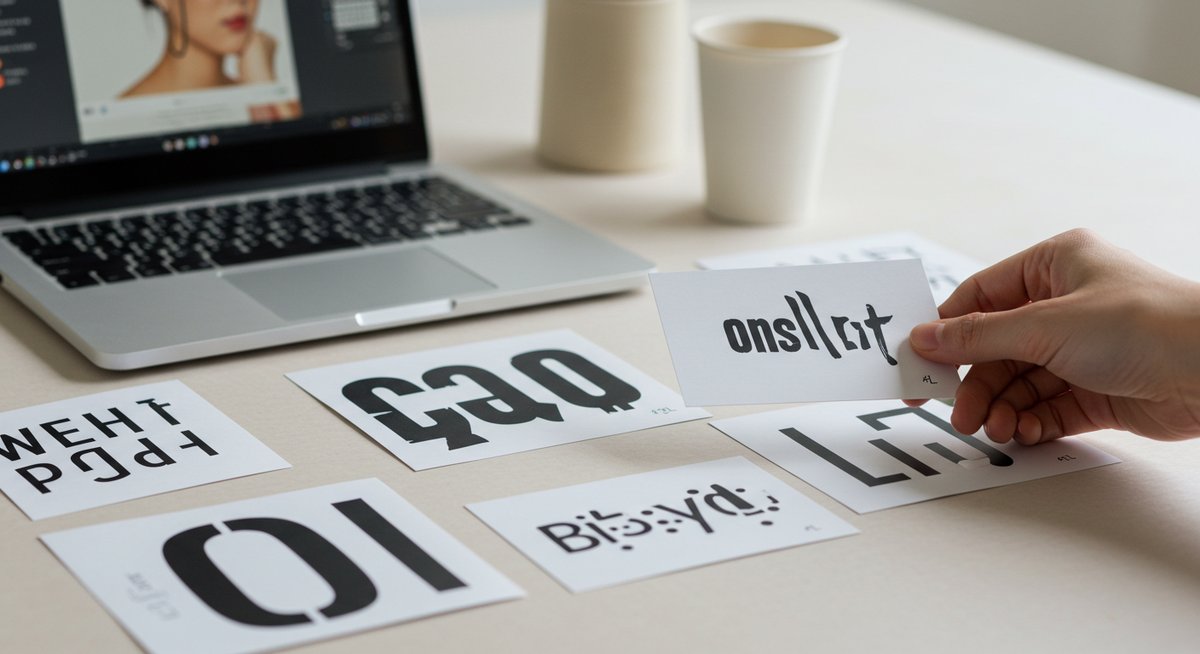
Canvaではフォントの選び方でデザインの印象が大きく変わります。用途や媒体、見せたい雰囲気を意識すると、読み手に伝わりやすくなります。ここでは見出し・本文・英数字など場面ごとに合うフォントを紹介し、確認や管理の手順までわかりやすくまとめました。どれを選べばよいか迷ったときの参考にしてください。
Canvaのフォントのおすすめを用途別に今すぐ選べるガイド
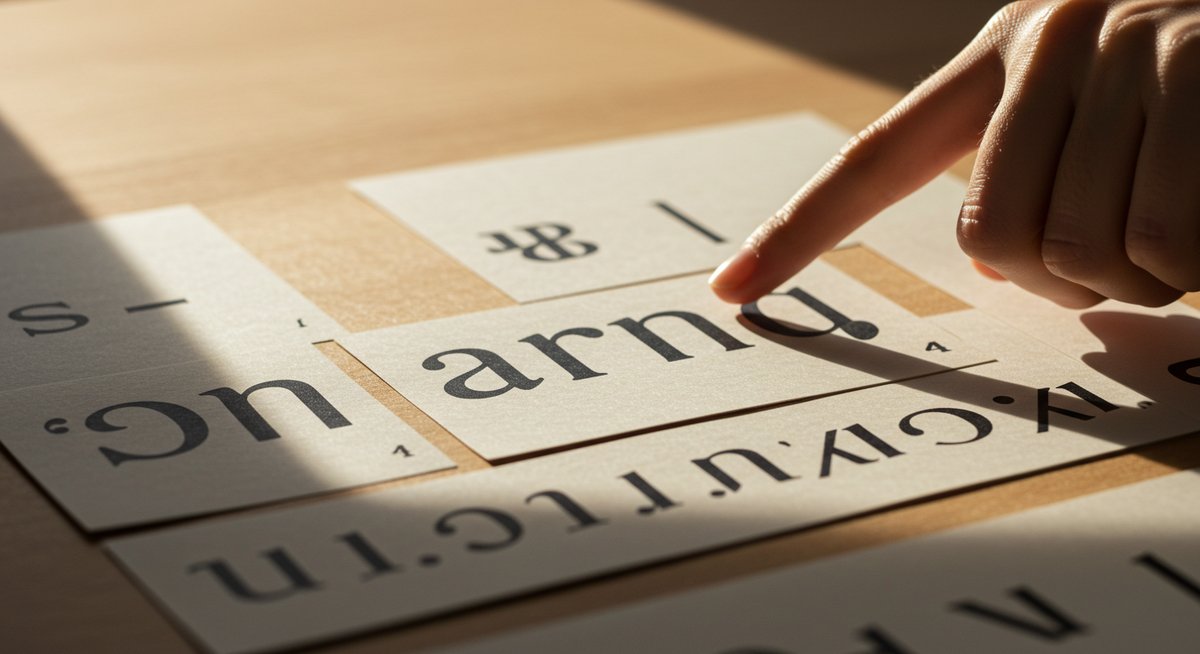
Canvaには多くのフォントが揃っていて、用途によって適したものが変わります。見出しで目を引きたいのか、本文で読みやすさを重視するのか、雰囲気づくりを優先するのかを決めてから選ぶと失敗が減ります。ここでは場面別に使いやすい候補を挙げますので、まずは用途をイメージしてみてください。
見出しを目立たせたいときの候補フォント
見出しは目を引くことが大切なので、太さや形がはっきりしたフォントが向いています。太めのゴシック系や重めのサンセリフは、遠くから見ても読み取りやすく、強い印象を与えます。読みやすさを落とさない範囲で字間をやや狭めにするとまとまりよく見えます。
見出しの候補としては、ウェイトが豊富で存在感のあるフォントを選ぶと使いやすいです。大見出しには太め、サブ見出しには中間のウェイトを使い分けると階層が出ます。さらに、色や装飾(影や縁取り)を控えめにすると読みやすさが保てます。
見出しを短めにして、余白を十分に取ることも重要です。文字が詰まりすぎると目立たなくなるので、行間や余白で調整しましょう。最終的には画面サイズごとに見え方を確認して決めるのがおすすめです。
本文を読みやすくするための候補フォント
本文は長時間読まれることを想定して選びます。線が細すぎたり装飾が強すぎると読みづらくなるので、シンプルで安定感のあるフォントが適しています。やや中〜細めのゴシックや、落ち着いたサンセリフ系が向いています。
行間は詰めすぎず広げすぎず、文字サイズに合ったバランスを取ると目が疲れにくくなります。改行や段落をこまめに入れて読みやすくすることも大切です。長文では字間を少し広めにすると視線の移動が楽になります。
また、本文に装飾を使う場合は強調したい語句だけに限定して、過度な色使いやスタイルは避けましょう。落ち着いた色と組み合わせると視認性が上がります。読み手の端末や環境に合わせて微調整することを意識してください。
カジュアルで親しみやすい雰囲気に合うフォント
親しみやすさを出したいときは、角の丸いゴシックや手書き風のフォントが合います。柔らかいラインや丸みのある字形は、人に近い印象を与え、フレンドリーなトーンのデザインにぴったりです。
ただし、カジュアル系フォントは行間や字サイズによって読みやすさが変わることがあります。見出しや短めのテキストで使うと雰囲気を出しやすく、長文にはシンプルな本文フォントと組み合わせるとバランスが良くなります。
色やアイコンと合わせて使うと雰囲気が強まります。元気に見せたいときは明るめの色、落ち着かせたいときはトーンを抑えた色でまとめると違和感が少なくなります。使う場面に応じて適度に調整してください。
上品な印象を作るフォントの選び方
上品さを出したい場合は、細めの明朝やスリムなサンセリフを検討すると良いです。文字の縦線と横線のコントラストが穏やかなものは、落ち着いた高級感を出しやすくなります。余白を十分にとることでより洗練された印象になります。
見出しに使う場合は太さのバリエーションがあるフォントを選ぶと、強弱をつけやすくなります。本文では細すぎると読みづらくなるため、中程度の太さを選びます。行間を広めに取って、余白で上品さを演出しましょう。
色はモノトーンや渋めのトーンが相性良く、装飾は最小限にとどめたほうが雰囲気が壊れません。写真や素材との組み合わせも意識して統一感を出してください。
数字や料金表示に合うフォントの簡単チェック
数字表示では桁ごとの視認性が重要です。等幅に近い数字や、数字の形がはっきりしたフォントを選ぶと読みやすくなります。特に価格や時間を示す場面では、数字の混同が起きないものを選びましょう。
チェック方法としては、同じフォントで複数桁の数字を並べて見比べることです。0とO、1とl(小文字のL)など紛らわしい文字がないか確認してください。視認性が弱いと誤解を生む可能性があるため、数字部分だけ別フォントで強めにするのも手です。
色や背景とのコントラストも確認してください。薄い色の背景に淡い数字は見えにくくなるので、コントラストを上げる調整をおすすめします。
用途や媒体で変えるCanvaフォント選びのコツ
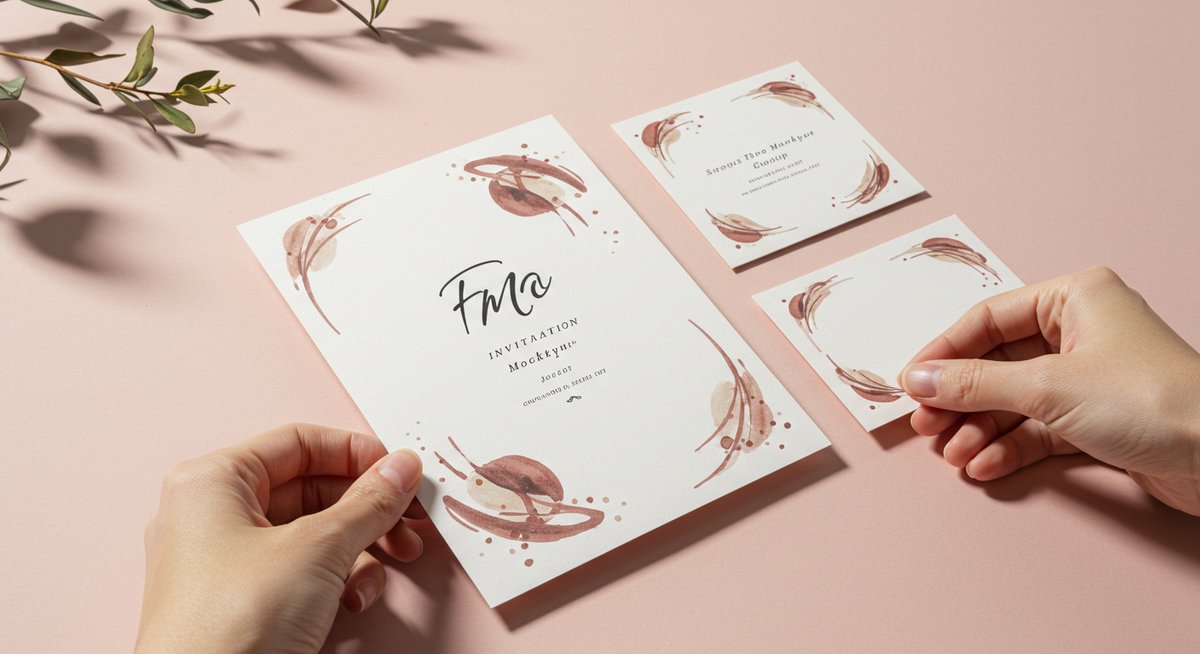
用途や媒体でフォントを変えると、伝えたいことが伝わりやすくなります。印刷物、Web、スマホ表示では視認性やサイズ感が違うため、それぞれに合った調整をすることが大切です。ここでは選び方のポイントと確認方法を紹介します。
見出しか本文かで役割を決める
まずは文字の役割をはっきりさせましょう。見出しは注意を引くために太さやサイズを重視し、本文は長時間読めるように落ち着いた形を選びます。役割ごとにフォントを分けることで視認性とデザインの一貫性が保てます。
見出しと本文で異なるフォントを使うときは、あまり種類を増やしすぎないことが肝心です。2〜3種類までに抑えるとまとまりがつきます。フォント同士の相性を見るときは、文字の太さや特徴がぶつからないかをチェックしてください。
組み合わせ例としては、太めのゴシック見出し+落ち着いたサンセリフ本文、丸ゴシック見出し+シンプルな本文などが使いやすいです。
スマホとPCで見え方を確認する
同じデザインでもスマホとPCで見え方が変わります。特に文字サイズや行間は端末ごとに最適な値が違うため、必ず両方で確認して調整しましょう。モバイル表示では文字が小さくなりがちなので、見出しはやや大きめに、本文は行間を少し広めにすることが多いです。
また、細いフォントは高解像度の画面でないとつぶれることがあるため注意してください。重要な情報は太めにして、色のコントラストも強めにすると読みやすくなります。実際にスクロールして確認してから公開するようにしてください。
ブランドの雰囲気に合うかを比べる
ブランドの印象とフォントは密接に関係します。信頼感を出したいなら整ったサンセリフ、親しみやすさを出したいなら丸みのある書体、といった具合に目的に合わせて選びます。既存のロゴやカラーと合わせて統一感を持たせることが重要です。
フォント選びの際は、ブランドの価値観やターゲット層を考慮して合うものを数種類ピックアップし、比較してみてください。違和感がないか、逆に個性がきちんと出ているかを見ると判断しやすくなります。
可読性を簡単にチェックする方法
可読性は実際に文字を並べて読みやすさを確認するのが早いです。長めの文章や数字、見出しを用意して、異なるサイズや行間で試してみましょう。複数の端末での表示も合わせてチェックすると安心です。
チェックリストとしては、文字の判別性、行間の余裕、色のコントラスト、強調部分の分かりやすさを確認します。読みやすさに不安がある場合は、別のフォントに切り替えるか、行間やサイズを調整してください。
用途別おすすめの日本語フォント一覧
用途別に日本語フォントの候補をリスト化します。デザインの目的に合わせて選ぶと作業がスムーズになります。読みやすさや印象の違いを意識して選んでみてください。
見出しに向く太字ゴシックの候補
見出し向けには太めで存在感のあるゴシックが適しています。文字の輪郭がはっきりしているため、遠目でも読みやすく、強調したい情報に向きます。
候補としては、太さのバリエーションがあるゴシック系、角がやや立った力強い書体、視認性の高い重めのフォントなどが使いやすいです。見出しサイズでの見え方を確認して選ぶと良い結果になります。
本文向けの読みやすいゴシック
本文には中〜細めのゴシックが向きます。線が均一で視線移動がスムーズなものが読みやすさにつながります。長文でも疲れにくいフォントを選んでください。
候補は、一般的にウェブや印刷で多く使われている定番のゴシックや、字間の処理が丁寧なフォントです。行間や文字サイズと合わせて調整すると快適に読めます。
上品に見せる明朝の代表例
上品な印象を出すなら明朝系が適しています。縦線と横線の強弱があるため、落ち着いた印象になりやすいです。表現を格調高くしたいときに効果的です。
候補は線のコントラストが穏やかなものや、細部が整った明朝書体です。見出しに使う場合はウェイトに注意し、本文用には中程度の太さが無難です。
柔らかさを出す丸ゴシックのおすすめ
丸ゴシックは角が丸く、柔らかく親しみやすい印象を作れます。幼児向けやカジュアルなブランドによく合います。読みやすさも保ちながら優しい雰囲気にできます。
候補は角丸のバランスが良いものや、文字の間隔が均等に処理されているフォントです。本文に使う場合はサイズや行間で調整して読みやすく仕上げてください。
手書き風で親しみが出るフォント
手書き風フォントは温かみと個性を出すのに向いています。ポップな案内や気軽なメッセージに合いますが、長文には向かないことがあります。
見出しや短いキャッチフレーズに使い、本文は別の読みやすいフォントを併用するとバランスが良くなります。字形のばらつきを確認して、読みづらくないものを選んでください。
有料で差が出るプロ向け日本語フォント
有料フォントは字形やウェイト、カーニング処理などが整っており、クオリティの高い表現が可能です。ブランドの顔として使う場面では導入を検討すると効果的です。
購入前にライセンス範囲を確認し、使用目的に合うか考えてください。サンプルを使って表示確認を行い、投資に見合う価値があるか判断しましょう。
英字や数字で差をつけるCanvaフォントの選び方
欧文や数字の扱いは印象を左右します。和文と組み合わせる際の統一感や、数字の見やすさに注意すると、全体のデザインが洗練されます。ここでは英字と数字の選び方をまとめます。
見出しで使いたいインパクトある英字
インパクトを出したい見出しには、太めのディスプレイ系や独特な個性を持つ英字フォントが向きます。装飾的な書体は短いフレーズで効果を発揮します。
ただし、長文には向かないため見出しやキャッチに限定して使うのが無難です。和文と合わせるときは、重量感や線の太さを合わせるとバランスが良くなります。
本文向け的の落ち着いたサンセリフ
本文の英字にはシンプルで読みやすいサンセリフが適しています。線が均一で視線の追随がしやすく、長文でも疲れにくい特徴があります。
和文の本文と組み合わせる際は、比率や行間を調整して統一感を出してください。小見出しや引用部分にはやや太めのウェイトを使うとアクセントになります。
数字表示を読みやすくする選び方
数字は桁ごとの判別がしやすいフォントを選ぶと安心です。プロポーショナル数字と等幅数字の違いがあり、料金や表組みでは等幅が適している場合があります。
通貨や時間を扱う場合は、数字だけ別フォントにするか、太さを変えて視認性を上げる工夫をしてください。背景とのコントラストも必ず確認しましょう。
筆記体やスクリプトの使いどころ
筆記体やスクリプトは高級感や手作り感を演出しますが、読みづらくなりがちです。短いタイトルやロゴ、装飾的な要素に限定して使うと効果的です。
本文や重要な情報には避け、視認性を崩さない範囲でアクセントとして取り入れてください。文字が重なる場合は字間を広げるなど調整が必要です。
和文と欧文の組合せで注意する点
和文と欧文を混ぜるときは高さや太さのバランスを合わせることが重要です。片方だけが強すぎると違和感が出るため、ウェイトや行間で整えると見栄えが良くなります。
英数字のサイズを和文に合わせて微調整すると統一感が出ます。最終確認は実際の画面で行い、違和感があれば微調整してください。
Canvaでフォントを追加して管理する流れと注意点
フォントの追加や管理は手順を知っておくと安心です。ここでは無料/有料の判別やアップロード方法、スマホ利用やライセンス確認、トラブル対応までを整理しました。
フォントが無料か有料かを見分ける方法
Canva内での表示やフォント配布元の情報を確認すると有料か無料かが分かります。配布元のサイトやライセンス表記をチェックして、商用利用の可否や制限を確認しましょう。
また、Canvaのプロプランで利用可能なフォントと、個別購入が必要なフォントがあるため、利用シーンに応じて確認すると安心です。見落としがちな使用条件に注意してください。
フォントをアップロードする基本手順
Canvaのデスクトップ版では外部フォントをアップロードできます。アップロード前にライセンスを確認し、対応フォーマットを用意してから行ってください。アップロード後はチームで共有する設定も可能です。
アップロード時はファイルサイズやフォントのバージョンに注意し、反映されない場合は再アップロードやブラウザのキャッシュクリアを試してみてください。
スマホアプリでフォントを使う方法
スマホアプリではCanva内のフォントを選んで使うことができますが、外部フォントのアップロードは制限がある場合があります。デスクトップでアップロードしておくとスマホでも使用できることが多いです。
アプリ上で表示崩れがある場合は、フォントのウェイトや行間を調整して見え方を整えてください。端末ごとの表示差にも注意しましょう。
今日から使えるCanvaフォントの選び方
最後にすぐ実践できるチェックリストをお伝えします。まずは用途(見出しか本文か)、媒体(スマホかPCか印刷か)、ブランドの雰囲気を決めます。候補を2〜3種類に絞り、実際にテキストを当てて見え方を確認しましょう。
次に行間・字間・色のコントラストを調整し、数字や英字の見え方もチェックします。ライセンスや費用を確認して問題なければ導入し、端末ごとの表示を最終確認してから公開してください。これだけ押さえれば、読みやすく伝わるデザイン作りがしやすくなります。